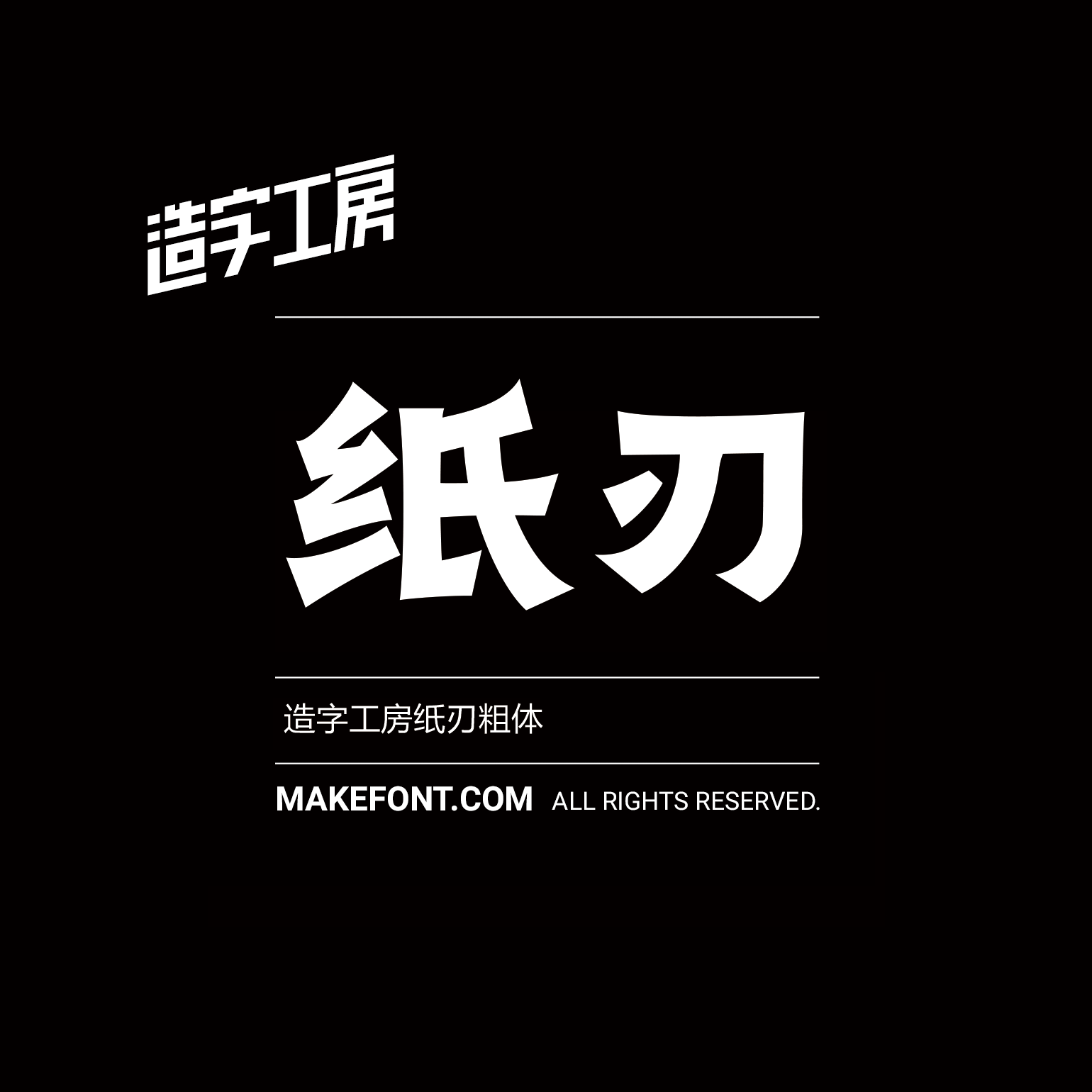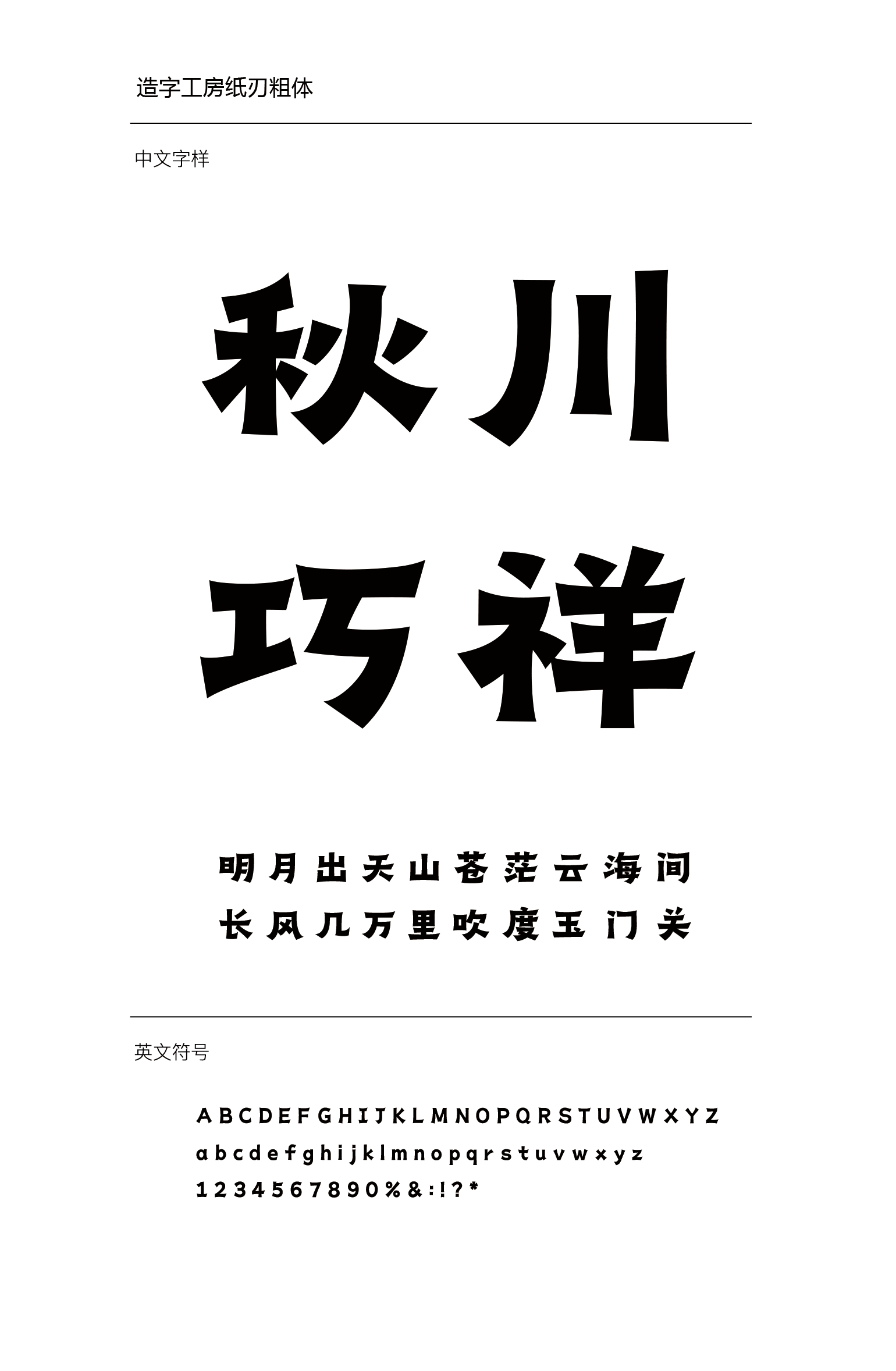
造字工房纸刃粗体
造字工房纸刃粗体设计说明
设计灵感来源于中国传统的民间手工艺—剪纸,结合了其“尖如麦芒、方如青砖”的线条特点,轮廓、形状坚实清晰,边缘似被剪裁过一样棱角分明,造型干练,兼具剪纸艺术镂空立体的美感和书法苍劲多姿的艺术享受,在保有传统剪纸艺术浪漫风格的同时,增加了笔画的墨法、线条的韵味。本字体为简体字库,采用OpenType/CID格式,Adobe-GB1-5编码。基于中华人民共和国GB2312-80字符集标准,另按需添加101个汉字。共收容字数6864CJK汉字,ASCII常用字符100个。